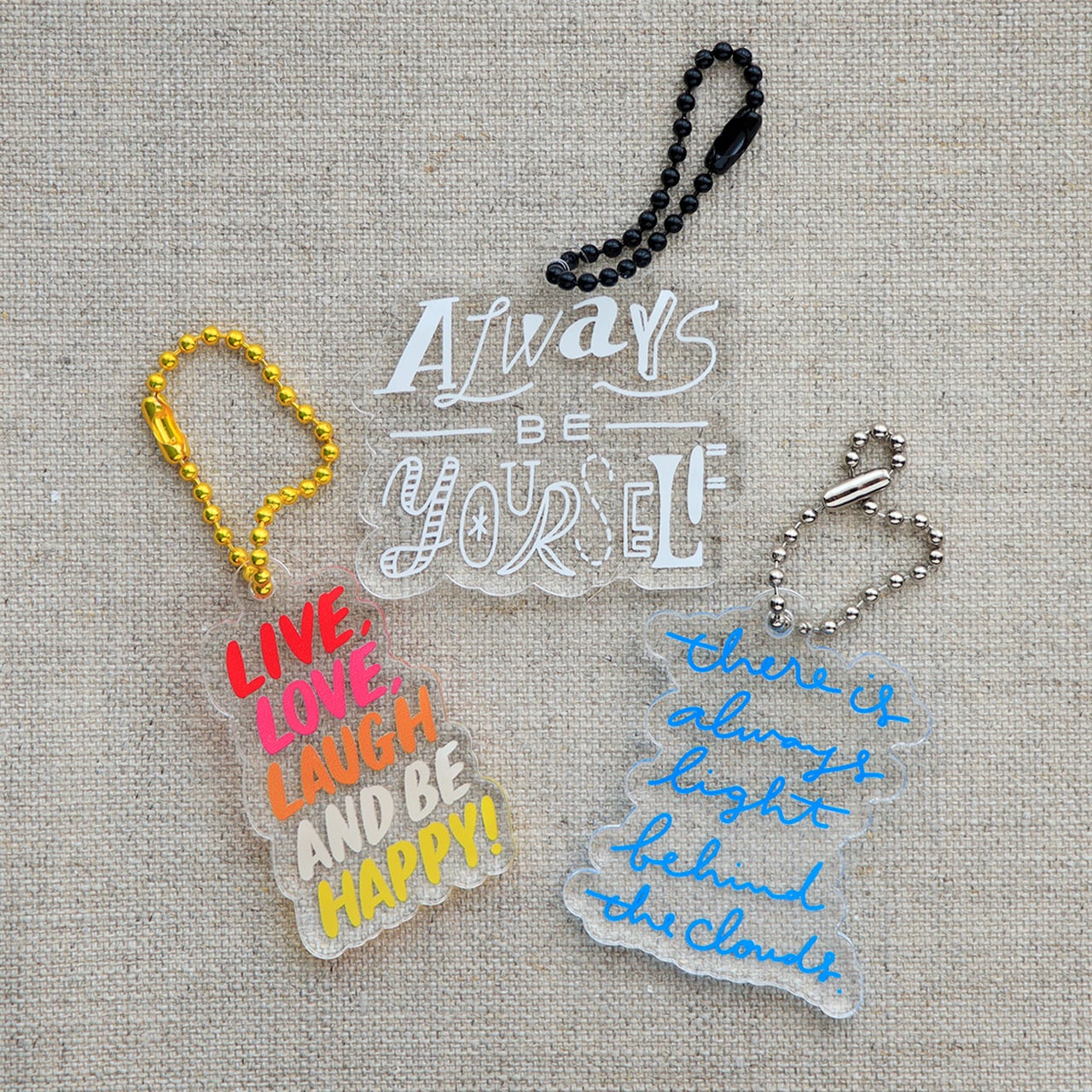
アクリルキーホルダー/Live, Love, Laugh and be Happy!
ポジティブになれる言葉のキーホルダー作りました
Live, Love, Laugh and be Happy!
愛して 笑って ハッピーな人生を!
ペイントの試作としてワインボトルに描いた言葉。
POP UPや展示に持っていくとよく褒められるので、いつでも持ち歩けるようにキーホルダーにしちゃいました!
カラフルでポップなフォントに合わせて、チェーンはゴールドにしました。